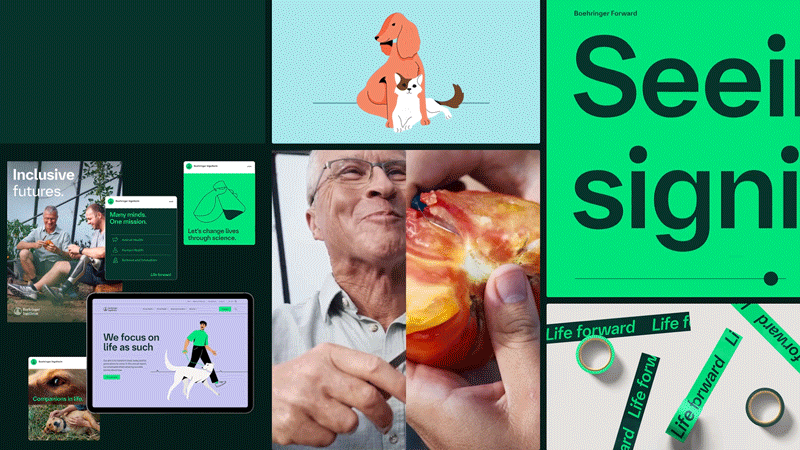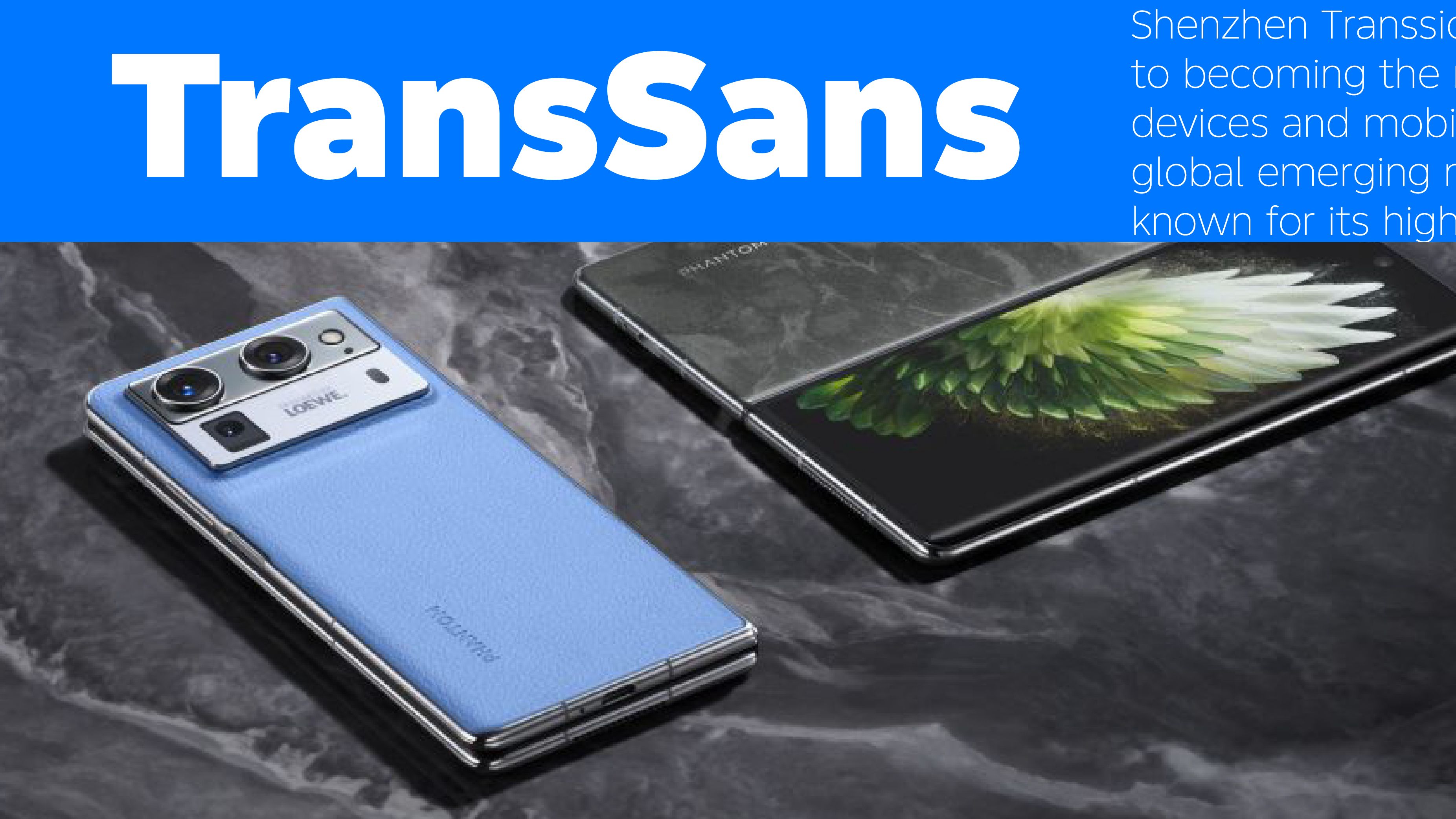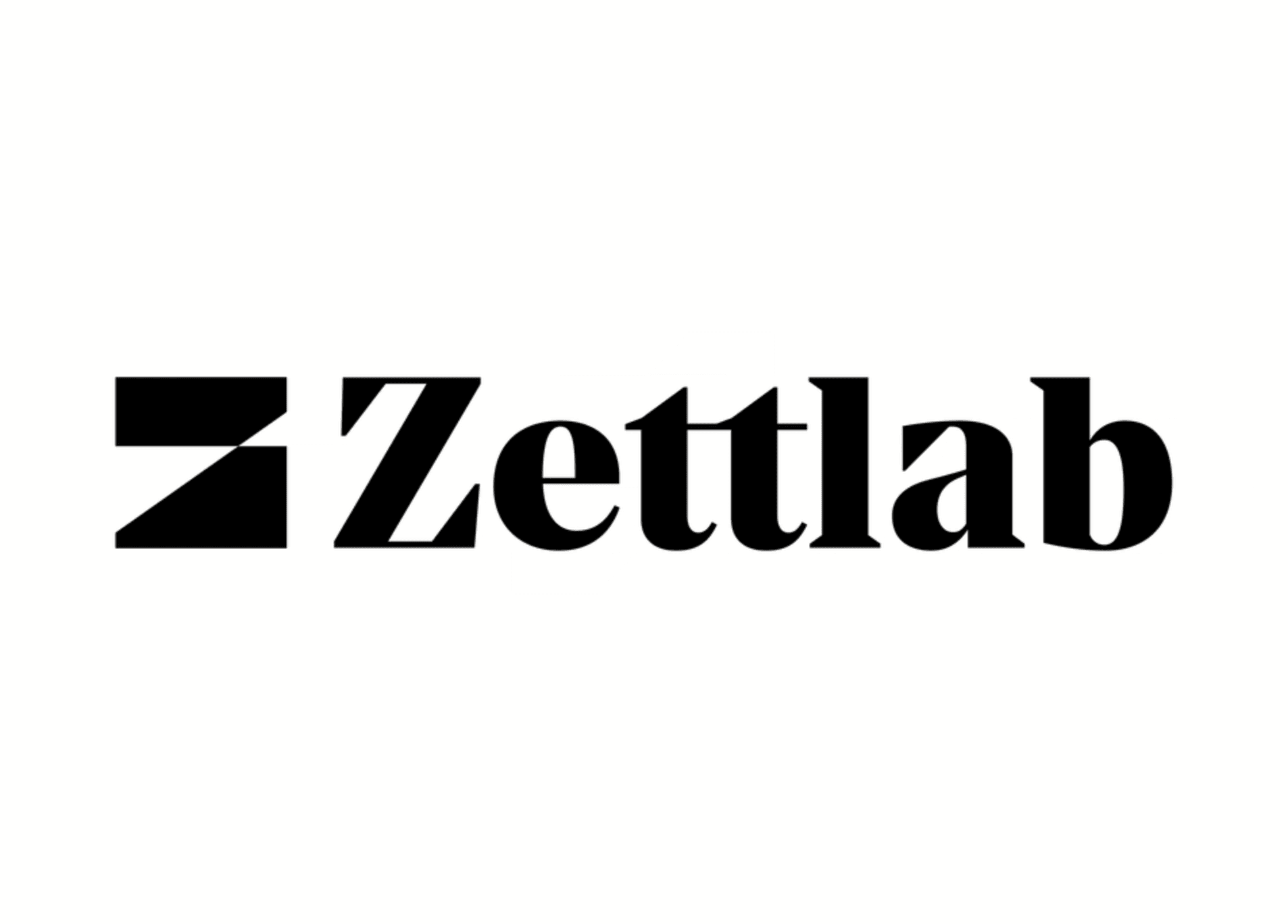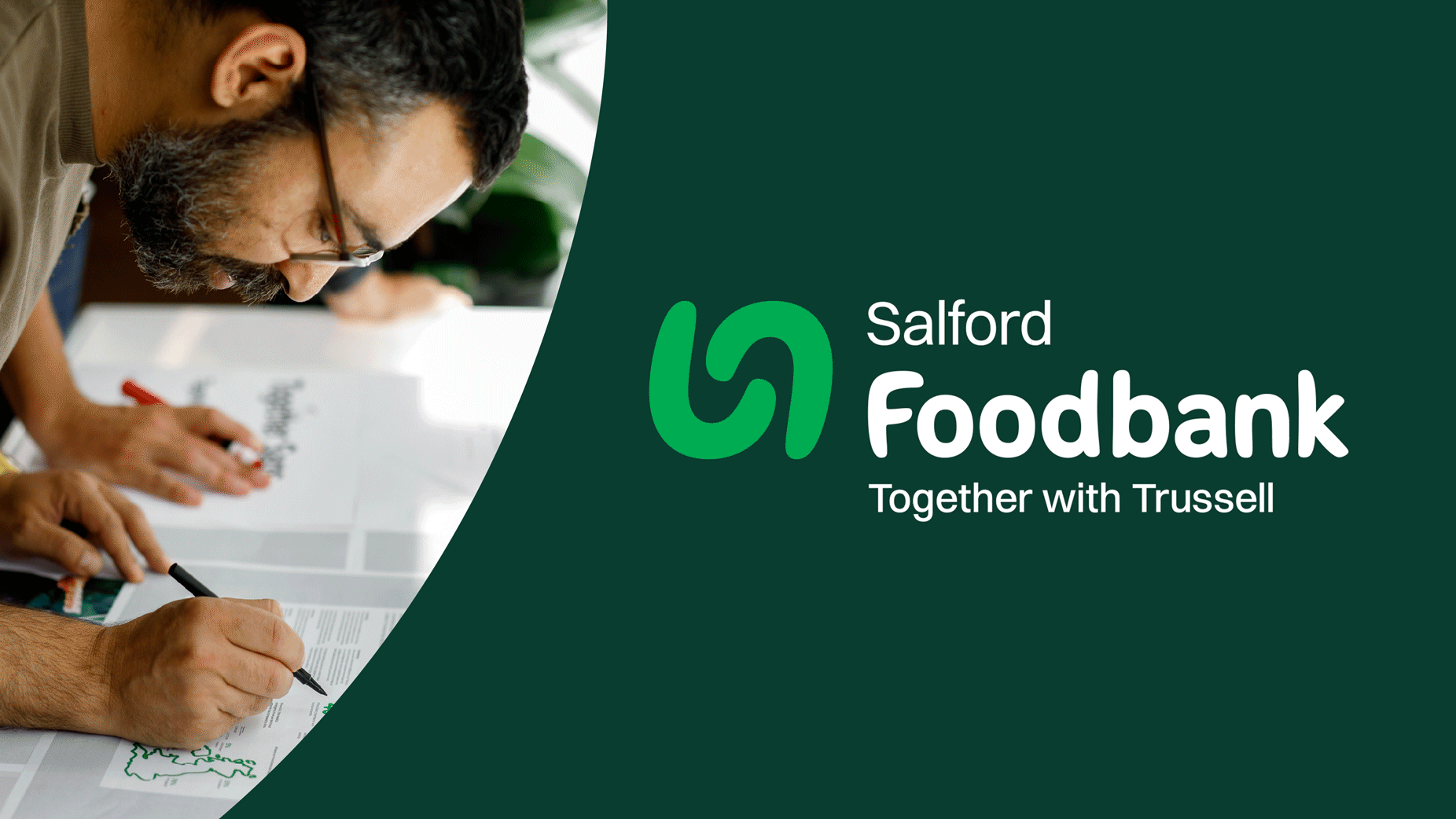
브랜드 경쟁이 점점 치열해지는 지금, 폰트는 더 이상 단순한 미적 요소에 머물지 않습니다. 폰트는 브랜드의 정체성과 감정을 드러내고, 기술 환경에 맞춘 전략까지 결정하는 핵심 자산입니다. 이 글에서는 다양한 실제 사례를 통해 폰트가 어떻게 브랜드 메시지를 강화하고 글로벌 시장 진출을 돕는지 살펴보고, 브랜드가 어떤 기준으로 폰트를 선택해야 하는지 실전적인 가이드를 제공합니다.
브랜드의 이미지와 영향력이 치열하게 경쟁하는 지금, 폰트는 더 이상 단순한 ‘장식’이 아닙니다. 폰트는 브랜드의 성격을 드러내고, 전달하고 싶은 가치를 설명하며, 소비자가 브랜드를 어떻게 느낄지까지 좌우하는 중요한 전략 자산입니다. 어떤 폰트를 고르고, 그것을 어떤 방식으로 활용하느냐에 따라 디지털 시대의 브랜드 인지도와 인상이 크게 달라집니다.
이 글에서는 TRANSSION(전신), Boehringer Ingelheim 등 국내외 브랜드 사례를 중심으로, 폰트를 어떻게 ‘말 없는 대변인’처럼 활용해 브랜드 전략에 녹여낼 수 있는지 집중적으로 살펴봅니다.
무언의 전략: 폰트는 어떻게 브랜드 정체성을 정의하는가?
브랜드의 톤 앤 매너를 이야기할 때 결국 핵심은 하나입니다. 소비자에게 어떤 감정을 느끼게 하고 싶은가? 신뢰감 있는 분위기인지, 혁신적이고 대담한 이미지인지, 아니면 따뜻하고 친근한 느낌인지. 폰트는 이런 추상적인 감정을 가장 직접적이고 빠르게 전달하는 시각 언어로, 브랜드가 어떤 존재인지 한눈에 보여주는 역할을 합니다.
Serif(세리프체): 글자 획 끝에 작은 장식선이 있는 폰트로, 구조가 단단하고 힘 있는 인상을 줍니다. 긴 글에서도 안정적인 리듬을 유지해 고전적이고 우아한 분위기를 만들기 때문에 책이나 잡지 같은 정식 출판물에서 자주 사용됩니다.Sans Serif(산세리프체): 장식 없이 깔끔한 선으로 이루어진 폰트입니다. 현대적이고 명료한 느낌을 주며, 화면에서도 가독성이 좋아 디지털 환경에서 특히 강점을 보입니다. 합리성과 효율성을 강조하고 싶을 때 잘 어울립니다.Script(스크립트): 손글씨 느낌이나 특정 테마를 직접적으로 표현하는 개성 강한 폰트입니다. 가독성이 다소 떨어지기 때문에 긴 본문보다는 제목이나 강조 요소처럼 시선을 끌어야 하는 부분에 적합합니다.
사례:
레드닷 수상, 크라우드펀딩 100만 돌파. AI 하드웨어 신예 브랜드는 어떻게 폰트로 글로벌 진출에 성공했나?
스마트 로컬 스토리지 분야에서 빠르게 성장한 기술 브랜드 Zettlab은 디자인 스튜디오 zerOh!와 협업해 Monotype의 Manier를 브랜드의 핵심 폰트로 채택했습니다. 기존의 기하학적이고 차가운 인상을 벗어나, Manier가 가진 리듬감 있는 획과 강렬한 세리프를 활용해 브랜드에 감정적 긴장감과 뚜렷한 존재감을 더했습니다. 이 선택은 브랜드의 시각적 성격을 명확히 하고 글로벌 시장에서 경쟁력을 높이는 데 중요한 역할을 했습니다.
감정의 연결: 폰트가 지닌 인간미
디지털 시대의 소비자는 단순한 정보보다 진정성과 감정적 연결을 더 강하게 기대합니다. 폰트는 브랜드의 인간적인 면을 드러내며 사용자와의 심리적 거리를 자연스럽게 좁혀주는 중요한 도구입니다.
예를 들어 Frutiger(프뤼티거)나 Gotham(고담) 같은 클래식 폰트는 손글씨 리듬에서 영감을 받아 약간의 불완전함이 남아 있는데, 이 미묘한 특징이 브랜드를 더 따뜻하고 친근하게 보이게 합니다. 또 특정 시대의 분위기를 담은 폰트를 사용하면 소비자의 기억과 감정을 자극해 편안하고 익숙한 느낌을 만들 수 있습니다. 그래서 가구, 뷰티, 식품 브랜드들은 ‘집의 온기’를 표현할 때 이런 감성 기반 폰트를 자주 활용합니다.
사례:
디자인이 ‘인문적 감성’과 ‘따뜻함’을 원할 때, 폰트는 어디까지 새롭게 시도할 수 있을까?
Monotype은 OPX Studio와 함께 영국에서 기아 문제 해결을 위해 활동하는 Trussell Trust를 위한 전용 서체 TogetherSans를 만들었습니다. 이 폰트가 특별한 이유는 일부 글자가 실제 자원봉사자와 지역 주민들이 행사에서 직접 적은 손글씨에서 영감을 받았기 때문입니다.
즉, 사람들이 직접 쓴 따뜻한 손글씨의 느낌을 폰트에 담아 브랜드가 전하고 싶은 ‘사람을 향한 진심’을 자연스럽게 드러낸 것입니다. 누구나 편안하게 느낄 수 있는 인간적인 분위기를 폰트 자체로 표현한 대표적인 사례입니다.
기술의 가능성: 폰트로 디지털 흐름에 적응하기
브랜드 폰트 전략은 단순히 로고나 색상을 바꾸는 수준이 아니라, 디지털 환경에 맞게 브랜드의 운영 방식을 다시 세우는 일에 가깝습니다. 기술이 발전하면서 폰트는 이제 브랜드를 떠받치는 중요한 인프라가 되었고, 훨씬 넓은 표현력을 제공하고 있습니다.
가장 대표적인 예가 바로 가변 폰트(Variable Fonts)입니다. 굵기, 너비, 기울임 같은 요소를 하나의 파일 안에서 자유롭게 조절할 수 있어 동적인 디자인이나 반응형 레이아웃을 만들 때 큰 효율을 줍니다.
또한 접근성(accessibility)도 중요한 기준으로 자리 잡았습니다. 화면 대비, 스크린 리더 지원, 다국어 문자 제공 같은 요소는 단순한 기술적 요건을 넘어, 브랜드가 얼마나 포용적이고 책임감 있게 소통하는지 보여주는 기준이 됩니다.
사례:
이름조차 읽기 어려운 글로벌 제약사, 어떻게 커스텀 폰트를 만들었나?
100년 역사의 Boehringer Ingelheim(베링거 인겔하임)은 브랜드 리뉴얼을 진행하면서, 대형 광고판처럼 큰 화면부터 의약품 안내서 같은 작은 인쇄물까지 모두 일관된 이미지를 유지할 수 있는 폰트가 필요했습니다. 이런 요구를 바탕으로 만들어진 폰트가 바로 Boehringer Forward입니다.
이 가변 폰트는 다양한 크기와 언어 환경에서도 브랜드가 지향하는 단단하고 긍정적인 이미지를 안정적으로 보여줍니다. 덕분에 어디에서 보더라도 같은 브랜드로 인식될 수 있는 통일된 시각 경험을 제공하게 되었죠.
해외 확장: 커스텀 폰트의 전략적 가치
브랜드가 한 시장에서 뚜렷한 이미지를 구축했다면, 다음 단계는 그 이미지를 글로벌 시장에서도 똑같이 전달하는 일입니다. 하지만 지역마다 언어와 문화가 다르기 때문에 브랜드의 톤과 분위기를 일관되게 유지하기가 쉽지 않습니다. 이런 상황에서 커스텀 폰트는 더 이상 선택적인 요소가 아니라, 실제 커뮤니케이션 문제를 해결해 주는 전략적 도구로 자리합니다.
맞춤 폰트를 사용하면 다양한 언어 환경에서도 브랜드의 목소리를 한결같이 유지할 수 있어, 세계 어디에서나 동일한 브랜드 경험을 만드는 데 큰 도움이 됩니다.
사례:
TRANSSION의 커스텀 폰트 TransSans: 다언어 환경에서의 브랜드 진화
여러 스마트폰 브랜드를 운영하는 TRANSSION(전신)은 신흥 시장마다 문자 구조가 크게 달라 기존 폰트만으로는 모든 언어에서 가독성과 일관성을 유지하기 어려웠습니다. 이 문제를 해결하기 위해 Monotype과 함께 TransSans를 개발했습니다.
TransSans는 다양한 문자 체계를 폭넓게 지원할 뿐만 아니라, 기술적인 완성도와 친근한 분위기를 동시에 갖춘 폰트입니다. 덕분에 TRANSSION은 여러 국가와 언어 환경에서도 안정적이고 전문적인 브랜드 톤을 유지할 수 있게 되었고, 글로벌 시장에서 더 일관된 브랜드 경험을 제공할 수 있게 되었습니다.
실전 가이드: 브랜드 폰트 선택의 네 가지 경로
전용 서체
브랜드가 충분히 성장했거나 장기적인 디지털 자산을 구축하려는 단계라면 맞춤 제작이 가장 적합한 선택입니다. 비용과 시간이 많이 들지만, 브랜드만의 고유한 개성을 완벽하게 구현할 수 있어 가장 강력한 차별화 효과를 제공합니다.
기존 폰트 수정
성장 단계에 있는 브랜드가 기본 폰트에 자기만의 색을 더하고 싶을 때 적합한 방식입니다. 비용 부담은 적지만, 충분히 개성 있는 결과를 만들 수 있어 실용성이 높습니다.
폰트 라이선스 구매
대부분의 브랜드, 특히 스타트업이나 빠르게 성장하는 기업에게 잘 맞는 선택입니다. 안정적이고 전문적인 품질을 확보할 수 있고, 선택할 수 있는 스타일도 다양해 바로 적용하기 좋습니다.
무료 폰트
프로토타입 제작이나 개인 프로젝트처럼 예산이 거의 없을 때만 적합한 방식입니다. 품질 차이가 크고 저작권이나 기술 지원 문제가 발생할 수 있어 장기적인 브랜드 구축에는 권장되지 않습니다.
폰트는 브랜드가 말 없이도 메시지를 전하는 핵심 자산입니다. 브랜드의 정체성을 보여주고 감정을 전달하며, 기술 변화 속에서도 일관된 경험을 만들 수 있게 합니다. Boehringer Ingelheim의 글로벌 일관성과 TRANSSION(전신)의 다언어 시장 대응 사례는 폰트 선택이 단순한 디자인 작업이 아니라 브랜드 전략 전반을 시각적으로 구현하는 과정임을 잘 보여줍니다.
커스텀 제작이든 기존 폰트 수정이든 라이선스 구매이든, 가장 중요한 점은 폰트가 브랜드의 가치와 자연스럽게 연결되어 어디에 쓰이든 같은 톤과 인상을 유지하는 것입니다. 모든 글자가 브랜드의 얼굴이 된다는 의미입니다.